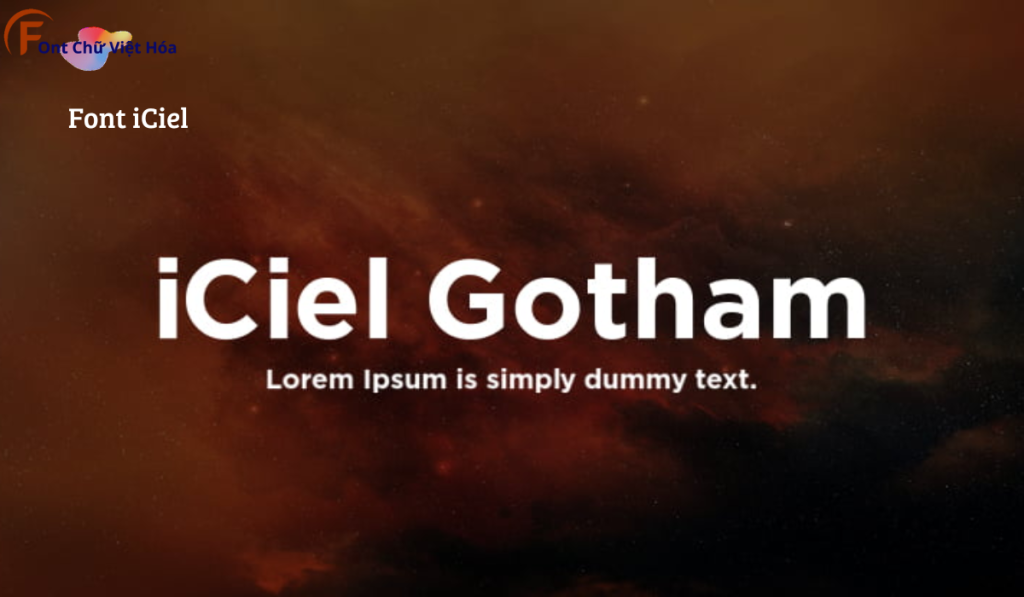
Font iCiel Gotham Việt Hóa
Bộ Font: iCiel
Phân loại: Hiện đại, Thanh lịch
Kiểu chữ: Sans-serif
Độ dày: Thin, Light, Regular, Medium, Bold, Black
Font iCiel Gotham Việt Hóa, thuộc bộ font iCiel, là font sans-serif hiện đại, nổi bật với các nét chữ rõ ràng và độ dày đa dạng. Font này có các đường nét gọn gàng, dễ đọc, tạo cảm giác chuyên nghiệp và tinh tế. Font iCiel Gotham Việt Hóa lý tưởng cho các dự án thiết kế như thiệp mời, bìa sách, và tài liệu văn phòng. Việc Việt hóa font giúp người dùng dễ dàng tích hợp vào các thiết kế tiếng Việt, mang lại sự tiện lợi và nâng cao tính thẩm mỹ.